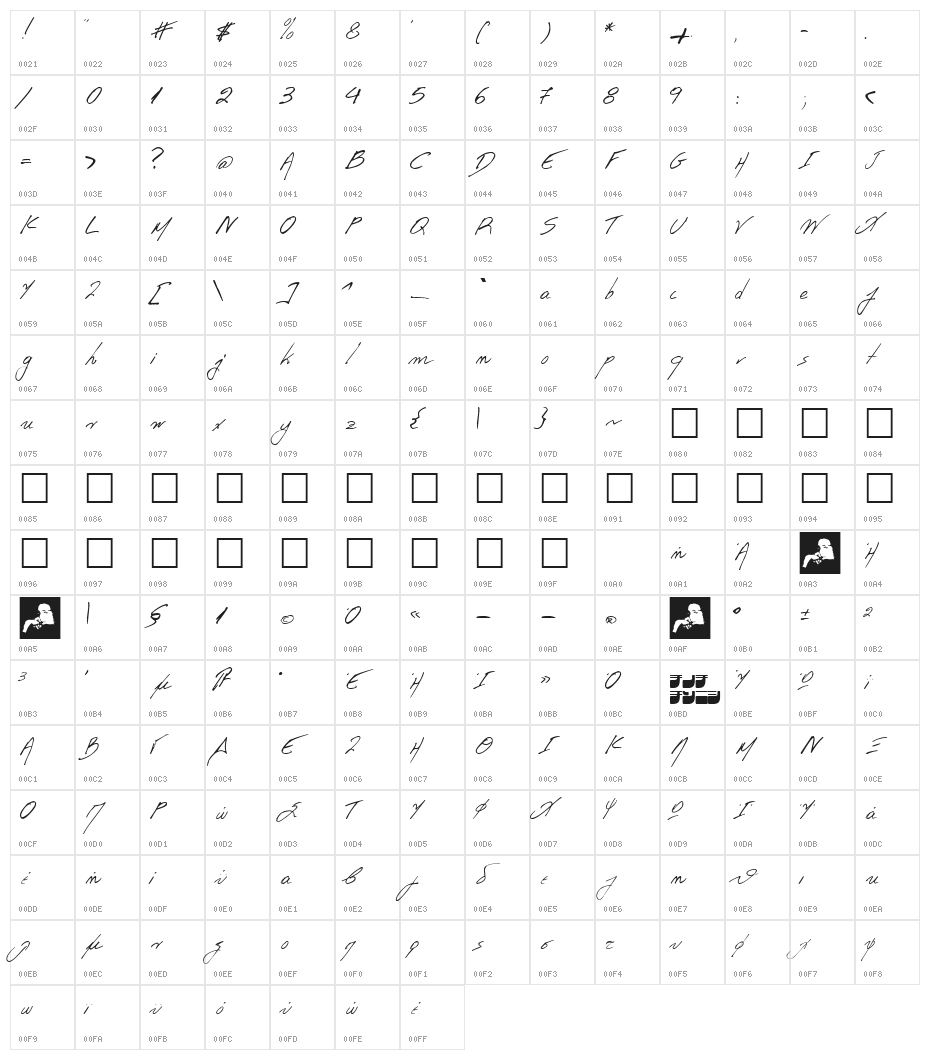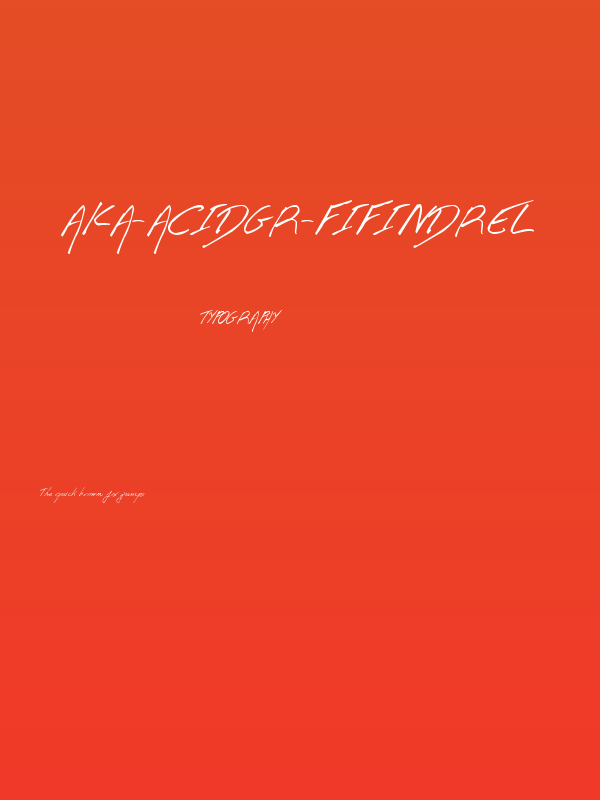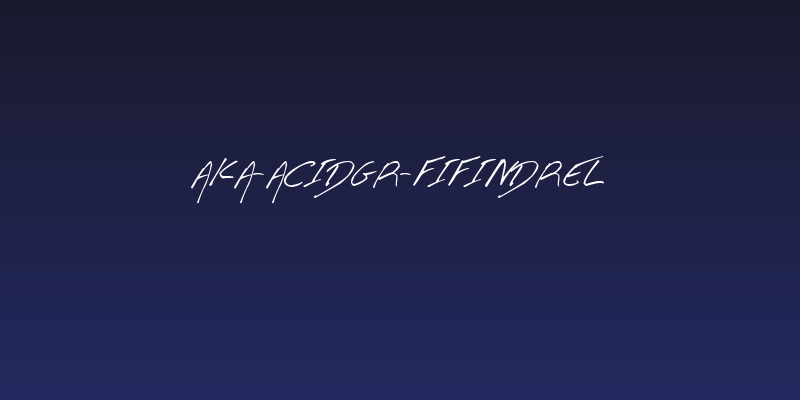
Aka-AcidGR-Fifindrel Font
| 全体的なスタイル | Elegant, Handwritten |
| 用途 | Logos, Invitations, Artistic projects |
| おすすめプロジェクト | Ideal for wedding invitations, personal branding, greeting cards, and artistic projects that require a personal touch. |